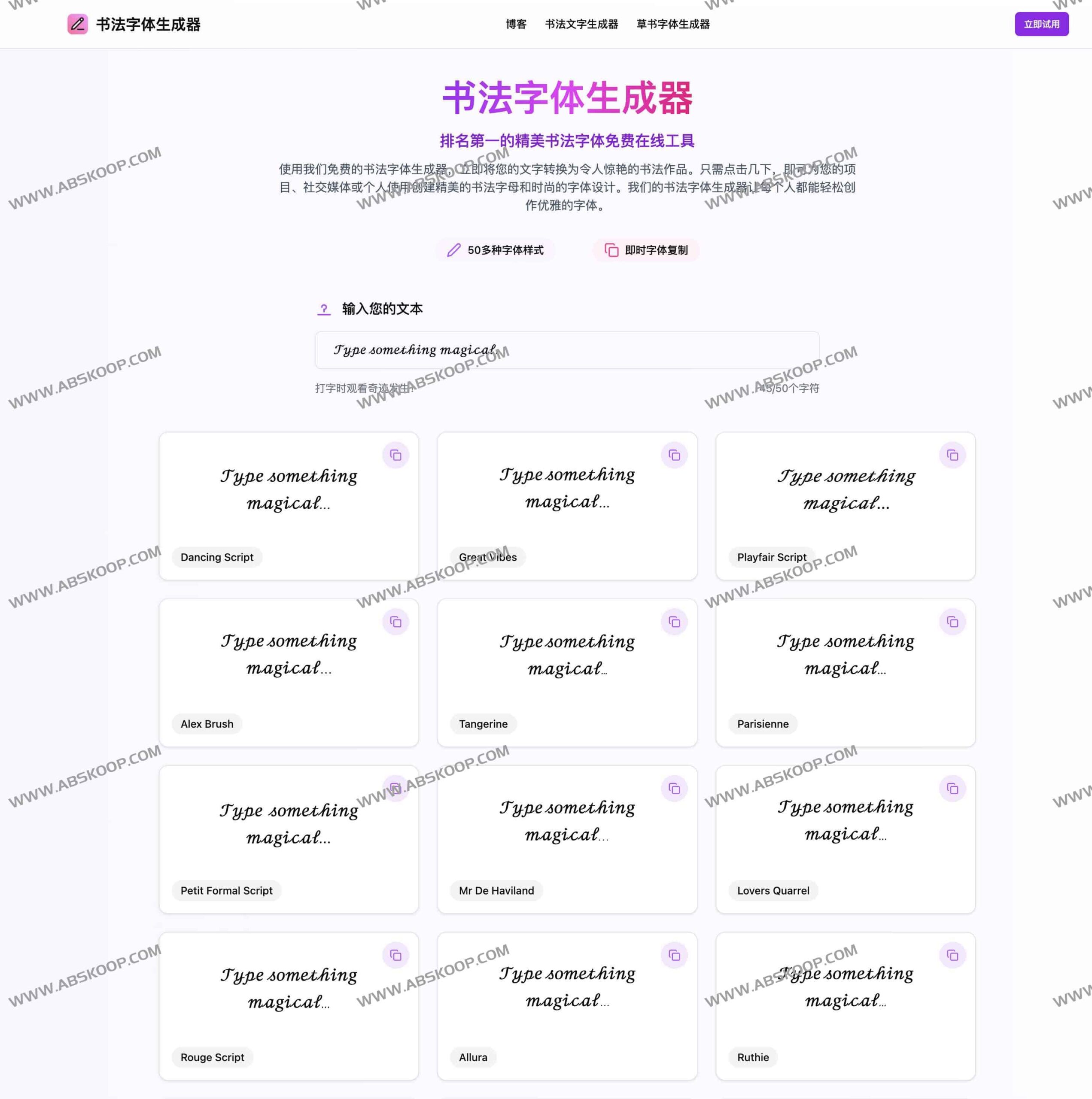
Calligraphy Font Generator:快速将文本转化为专业书法艺术
Calligraphy Font Generator 是一款高效的免费在线工具,旨在通过 50 多种精选的书法样式,让没有任何设计基础的用户也能瞬间将普通文本转化为极具美感的视觉作品。该工具不仅支持实时预览与深度定制,且全面兼容商业用途,是提升设计质感的快捷之选。
核心功能解析
多样化的风格库
平台内置 50 余种书法字体,涵盖了从古典优雅到现代简约的多种美学风格。用户可根据项目的具体氛围选择单款字体,或尝试多种风格混搭,打造出独特的视觉层次感。
灵活的实时定制
输入文字后,渲染效果即时呈现。用户可以对以下参数进行精细化调整,确保排版完美:
• 视觉属性: 自由定义字体颜色与大小。
• 排版细节: 灵活微调字距(Letter Spacing)与行高。
• 背景设置: 提供多种预设背景,并支持 透明背景 导出,极大方便了后续的图像合成与叠加。
全场景导出方案
进阶亮点
• AI 智能匹配: 系统能根据文本内容与设定的使用场景,自动推荐最契合的书法样式,缩短筛选时间。
• 专业签名模块: 专门的签名生成功能,提供多种笔迹风格与模板,可快速创建用于电子文档或品牌宣传的数字签名。
• 精准排版控制: 支持对单字或全句进行微米级的间距微调,消除视觉上的拥挤感。
• 字体配对建议: 智能推荐辅助字体,帮助用户在处理多级标题与正文时,实现和谐的视觉搭配。
适用场景
• 高端礼品与文具: 制作典雅的婚礼请柬、座位卡或私人邀请函。
• 社交媒体运营: 创作具有辨识度的金句海报、个人简介或品牌标签。
• 品牌视觉开发: 为 Logo 设计、定制 T 恤及周边商品添加个性化书法文字。
• 数字艺术创作: 将艺术文字融入插画,或生成专业级数字签名。